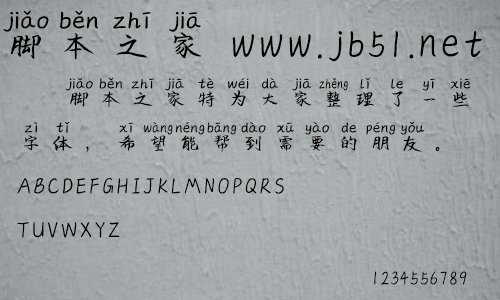
義啟芝士就是力量是由義啟字庫(kù)出品的帶拼音的藝術(shù)字體,這款字體筆觸粗細(xì)適中,字形端正,具有很好的視覺(jué)感,適合應(yīng)用于藝術(shù)設(shè)計(jì)、平面宣傳設(shè)計(jì)、網(wǎng)頁(yè)設(shè)計(jì),書(shū)法字帖等領(lǐng)域,需要的朋友可以前來(lái)本站下載。